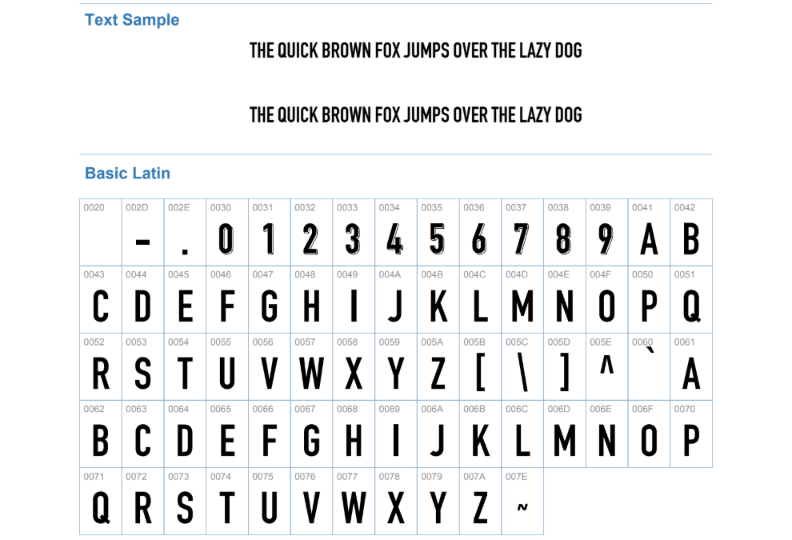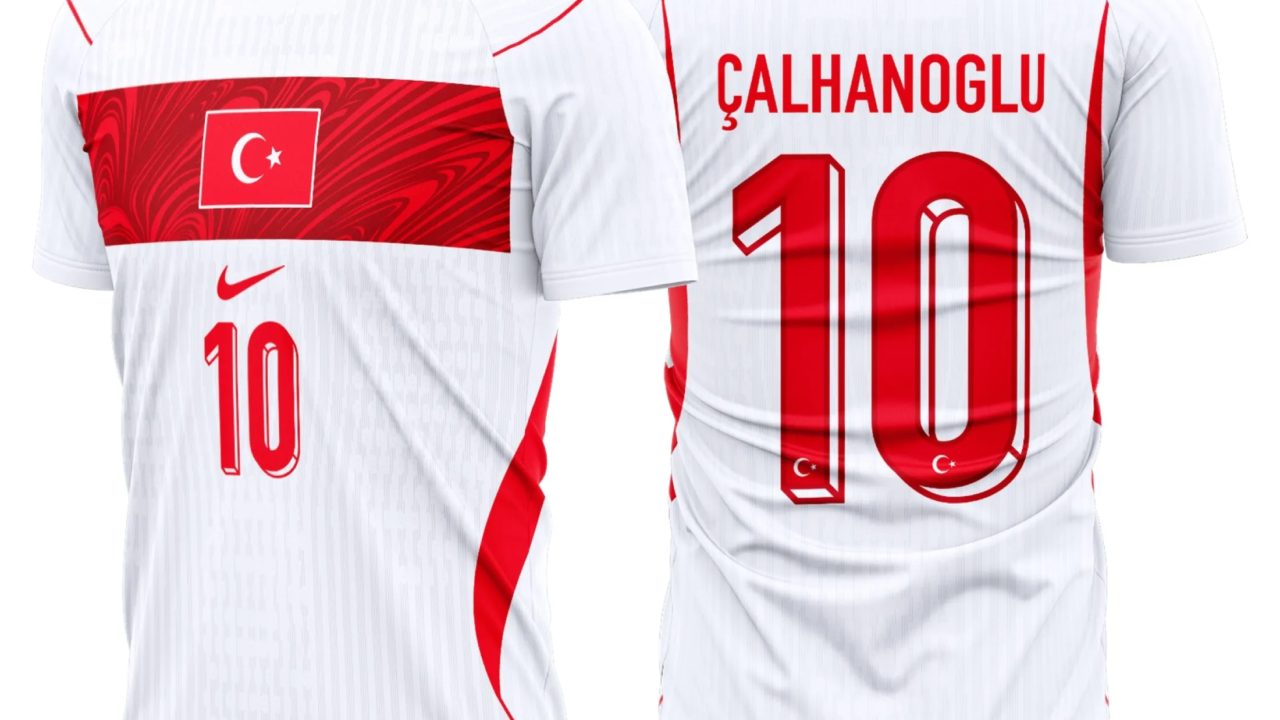
A Turquia está de volta à Copa do Mundo após 24 anos, e a expectativa da torcida vai muito além do gramado. A seleção comandada por Vincenzo Montella herdou um grupo jovem e talentoso, com nomes como Arda Güler, Kenan Yıldız e Hakan Çalhanoğlu – e a identidade visual do time precisava acompanhar esse momento histórico.
É nesse cenário que a tipografia oficial da Turquia para a Copa do Mundo 2026 ganha destaque. Fãs e designers de todo o mundo já buscam a fonte que estampa os novos uniformes, seja para criar mockups, artes para redes sociais ou projetos gráficos com a cara da seleção.
Detalhes técnicos da fonte
Estilo visual da tipografia
A fonte da Turquia para 2026 é alta, condensada e altamente legível. Sua construção vertical limpa garante que os nomes dos jogadores fiquem nítidos tanto em close-ups quanto na visão ampla do uniforme.
Os números são bold e levemente esculpidos, com sombras angulares que adicionam profundidade sem pesar no design. O acabamento em branco cria contraste forte contra o fundo vermelho do uniforme principal. Um dos detalhes mais marcantes é o pequeno emblema de crescente e estrela posicionado abaixo dos numerais – um toque de identidade nacional que faz toda a diferença.
Aplicação no uniforme
- Home (titular): Vermelho tradicional, com números e letras em branco de alto contraste.
- Away (reserva): Off-white com detalhes em vermelho, seguindo a mesma tipografia moderna.